Font Comic Việt hóa là nhóm phông chữ đặc thù được lấy cảm hứng từ nghệ thuật vẽ chữ thoại trong các cuốn truyện tranh và phim hoạt hình, nổi bật với các nét vẽ tay ngẫu hứng, đường cong tự do và năng lượng tươi vui, gần gũi. Mang vẻ ngoài hóm hỉnh, thân thiện và giàu tính biểu cảm, font Comic Sans Việt hóa cùng các biến thể phông hoạt hình là chất liệu trực quan tuyệt vời để các kiến trúc sư, nhà thiết kế mang lại sự ấm áp cho các bản vẽ phối cảnh trường mầm non lắp ghép, quán cà phê truyện tranh container hay khu vui chơi trẻ em tại các homestay gia đình.
Nhịp điệu thoại kịch sống động và nét vẽ tay ngộ nghĩnh của font Comic Việt hóa
Điểm cuốn hút của font Comic Việt hóa nằm ở sự phá vỡ các quy chuẩn hình học đối xứng nghiêm ngặt để tái hiện sinh động cảm xúc tự nhiên của lời nói thường ngày. Các con chữ sở hữu độ nghiêng nhẹ nhàng, nét bo tròn ở các góc cạnh và sự xê xích vui mắt giữa các ký tự, gợi liên tưởng đến những bong bóng lời thoại ngộ nghĩnh trong truyện tranh.
Sự ổn định về mặt cảm xúc của dòng font này giúp giải tỏa căng thẳng, tạo bầu không khí thư thái và kích thích sự tương tác cởi mở giữa con người với không gian. Khi kết hợp cùng các vật liệu kiến trúc hiện đại như vách tôn sóng container sơn màu tươi sáng, tấm alu vàng chanh, sàn nhựa vân gỗ hay kính dán decal hoạt họa, phông chữ Comic tạo nên sự tương thích thẩm mỹ đầy năng lượng.
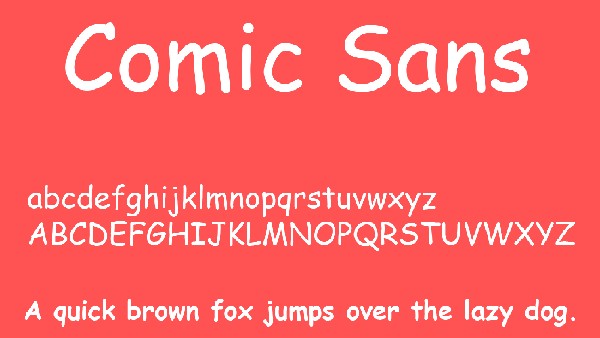
03 Ứng dụng phông chữ Comic vào công trình thực tế
Nhờ vẻ ngoài vui nhộn và tính gợi cảm xúc thân thiện, bộ phông chữ này mang lại giá trị thực tế lớn trong khâu tạo điểm nhấn cho các công trình hiện đại:
- Hệ thống biển hiệu cho Quán Cà phê Truyện tranh và Boardgame Container: Những con chữ ngộ nghĩnh của Comic rất ăn ý khi gia công chữ nổi bằng mica màu sắc gắn đèn LED trên vách tôn, mang lại diện mạo trẻ trung, thu hút các bạn trẻ ghé thăm giải trí.
- Bảng chỉ dẫn và Biển tên phòng Trường mầm non Lắp ghép: Phông chữ này khi in trên các bảng alu màu pastel hoặc decal dán tường sẽ giúp không gian lớp học toát lên sự thân thiện, tạo sự hào hứng cho các bé mỗi ngày đến trường.
- Trang trí góc đọc sách và Không gian sinh hoạt gia đình Homestay: Sử dụng font HL Comic Việt hóa để làm tranh trích dẫn hài hước hoặc bảng nội quy thân thiện giúp các căn phòng nghỉ dưỡng toát lên nét ấm cúng và gần gũi.
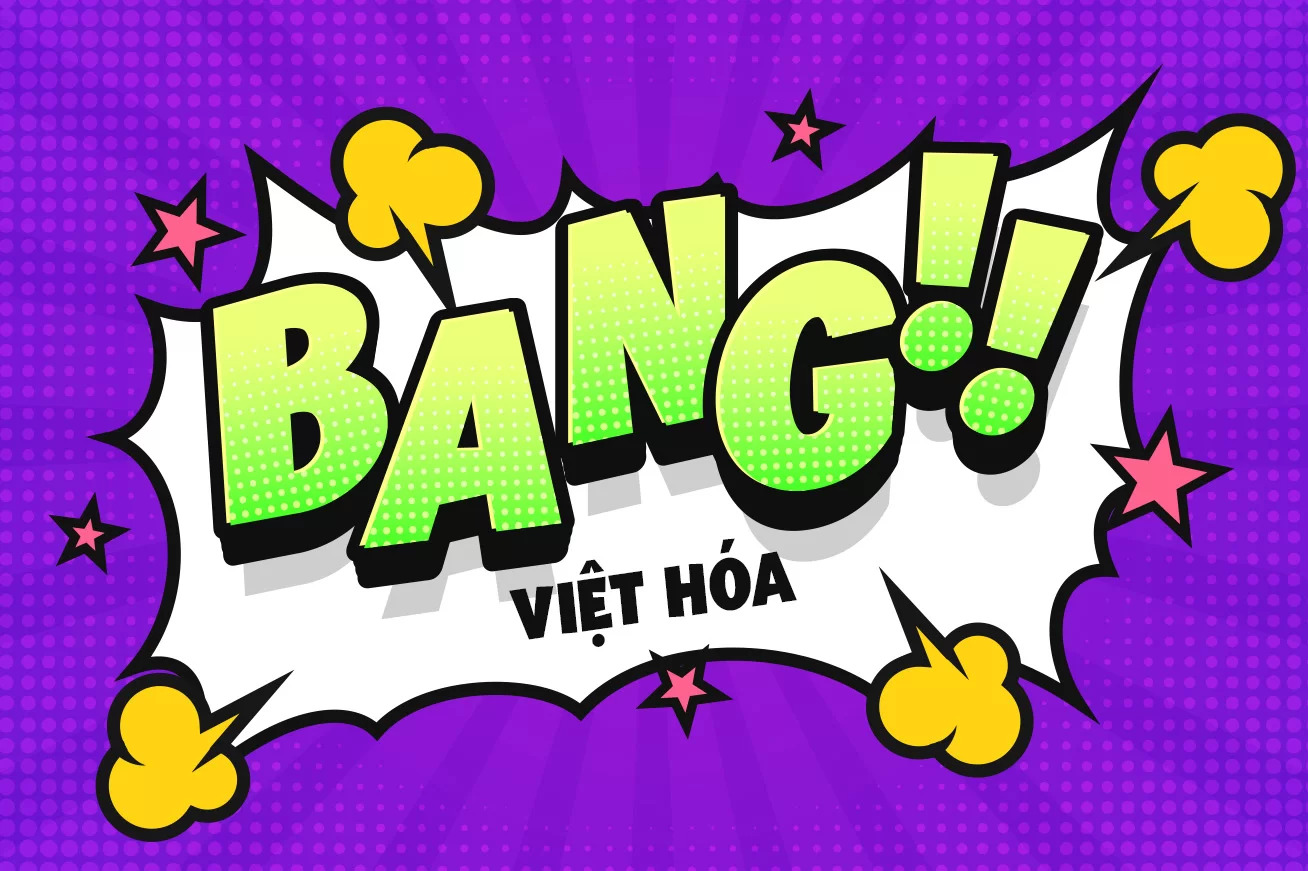
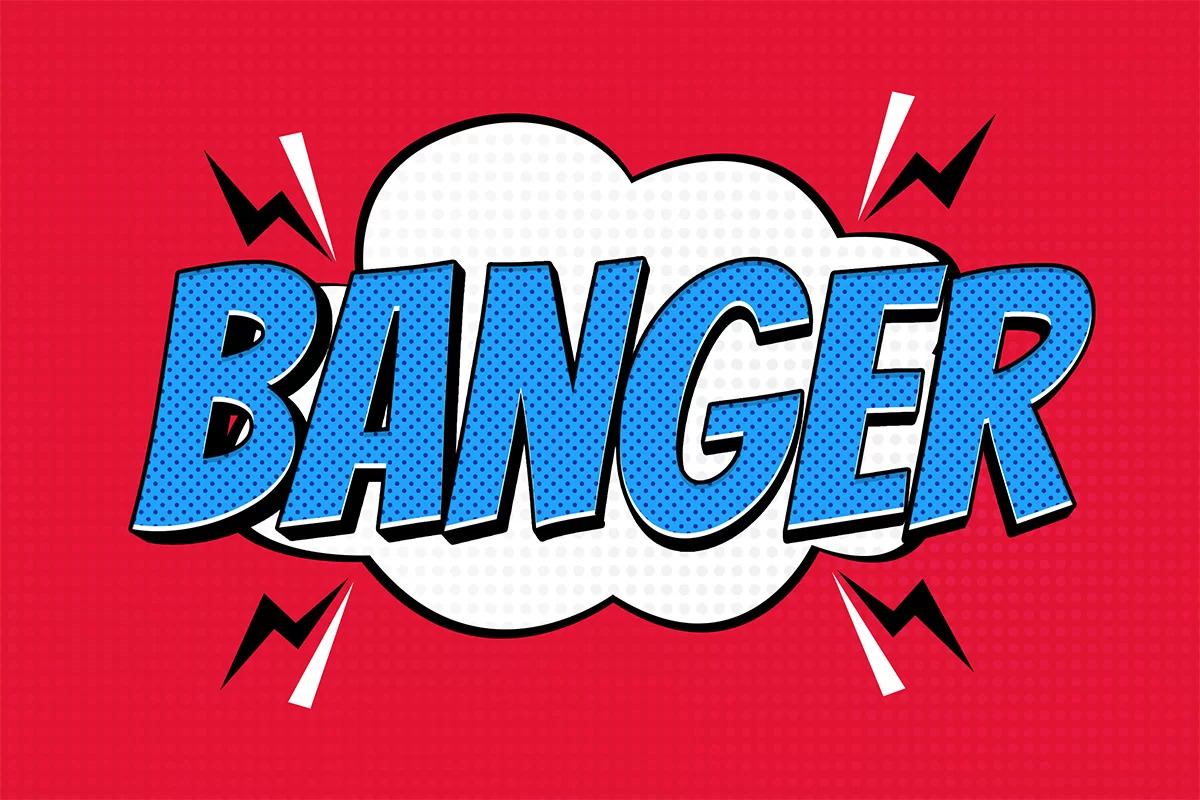
03 Lưu ý bố cục font Comic Sans Việt hóa luôn tươi vui và dễ đọc
Để khai thác hiệu quả vẻ đẹp của dòng font truyện tranh này mà không gây cảm giác lộn xộn cho bản vẽ, người thiết kế nên lưu tâm một số kinh nghiệm sau:
- Bố trí khoảng thở tự nhiên: Cấu trúc các ký tự của Comic có độ nghiêng và độ cao không đồng đều. Bạn nên chừa khoảng trống xung quanh tiêu đề thoáng đãng để các con chữ có không gian bộc lộ tính ngẫu hứng, tránh chèn ép bởi các khung viền cứng nhắc.
- Hạn chế dùng cho hồ sơ kỹ thuật nghiêm trang: Tính chất vui nhộn của Comic không phù hợp cho các văn bản pháp lý hay bản vẽ kết cấu chịu lực. Hãy giới hạn sử dụng trong các khu vực giải trí hoặc biển hiệu mang tính tương tác cộng đồng.
- Kết hợp cùng gam màu rực rỡ: Phông chữ phát huy hiệu quả thị giác cao khi phối cùng các tông màu tươi sáng như vàng chanh, xanh da trời, cam cà rốt hoặc đỏ tươi trên nền trắng kem, làm nổi bật phong cách truyện tranh của bộ chữ.